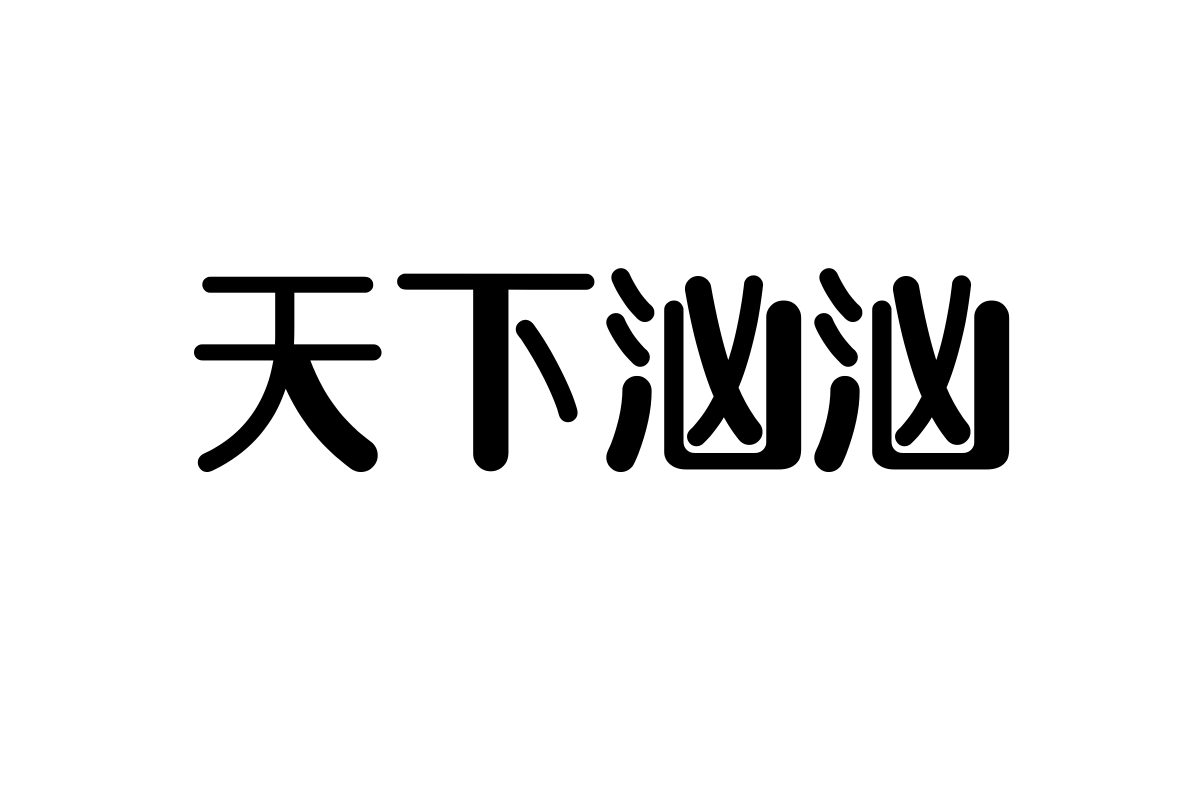
上首喵尾体是一种独特的字体,它的特点是在传统的汉字基础上进行了创新和改良,使得每个字符都呈现出一种独特的美感。这种字体的特点包括:
1. 结构独特:上首喵尾体的字形结构不同于传统的汉字,每个字的笔画都经过精心设计,使得整个字体看起来既有美感又具有艺术性。
2. 线条流畅:这种字体的线条流畅自然,没有生硬的感觉,给人一种舒适的感觉。
3. 易于识别:由于这种字体的结构独特,所以很容易辨认,不需要花费太多的时间去记忆。
4. 适用性强:这种字体适用于各种场合,无论是正式的商务场合还是休闲的娱乐场合都可以使用,具有很强的适应性。
总的来说,上首喵尾体是一种非常独特的字体,它的出现无疑为汉字的发展注入了新的活力。